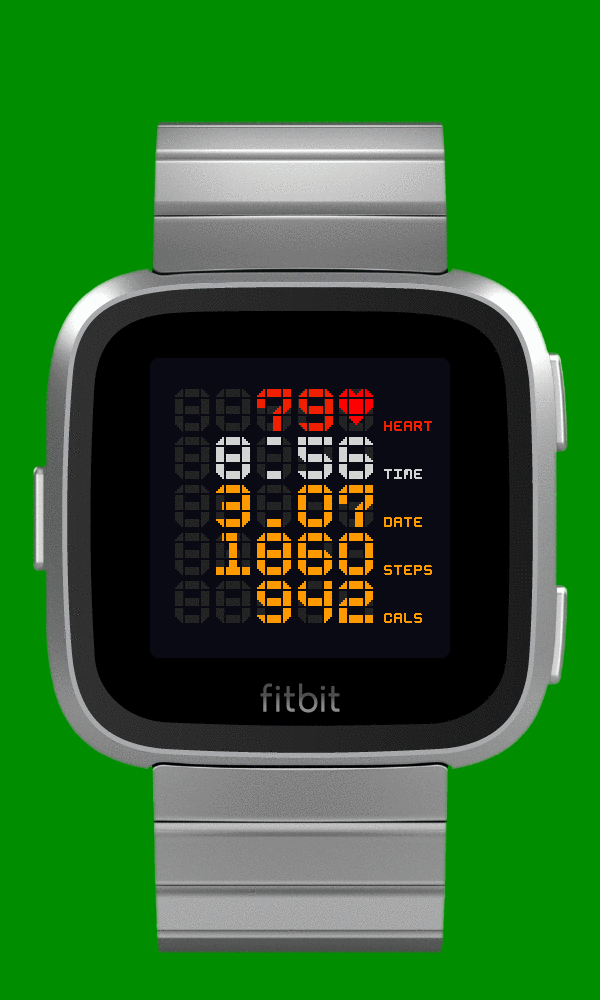
Suche Font des TTMMBRN NOW Fitbit Clock Face
Hallo @SandraMichael, wofür genau suchst du den Font? Es kann gut sein, dass es sich bei dieser speziellen Abbildung nicht um eine frei verfügbare Satzschrift handelt.
Wenn es eine ähnliche Schrift sein darf, schau dir einmal die »Bus« an (Lars Harmsen, 2004) oder geh die Suchergebnisse zum Tag »Segment« beim Schrifthandelshaus deines Vertrauens durch.
Die Schrift ist auch sehr chic! Aber ich hätte lieber das Original.
Vielleicht hat sie der Designer tatsächlich selbst entworfen...
Da Albert Salamon, der Anbieter von ttmbrwn now, anscheinend ausschließlich Uhren-Interfaces vertreibt, könnte die Konstruktion eigener Ziffern als usp tatsächlich zu seinem Selbstverständnis als Designer gehören. Aber im Zweifelsfall einfach direkt bei ihm nachfragen, wie von @Phoibos vorgeschlagen.